Typografie
Typografie (vom Duden und der schweizerischen Bundeskanzlei empfohlene Schreibweise)[1][2] oder Typographie (von altgriechisch τύπος týpos „Schlag, Abdruck, Figur, Typ“ und -graphie) ist eine mehrdeutige Bezeichnung: Im traditionellen Sinne bezieht sie sich auf die Gestaltung von Druckwerken mit beweglichen Lettern (Typen). In der Medientheorie steht Typografie für gedruckte Schrift in Abgrenzung zu Handschrift (Chirografie) und elektronischen sowie nicht literalen Texten.
Ein Buchdrucker der Frühen Neuzeit wurde als typographus bezeichnet, womit im 16. und 17. Jahrhundert auch als Verleger tätige Drucker (Drucker-Verleger) gemeint sein konnten.[3] Heute bezeichnet Typografie meist den medienunabhängigen Gestaltungsprozess, der mittels Schrift, Bildern, Linien, Flächen und Leerräumen alle Arten von Kommunikationsmedien gestaltet. Typografie ist in Abgrenzung zu Kalligrafie, Schreiben oder Schriftentwurf das Gestalten mit vorgefundenem Material.
Die Typografie wird unterteilt in Mikrotypografie und Makrotypografie. Die Arbeit des Typografen besteht darin, beide Gestaltungsmerkmale in geeigneter Weise zu kombinieren.
Mikrotypografie
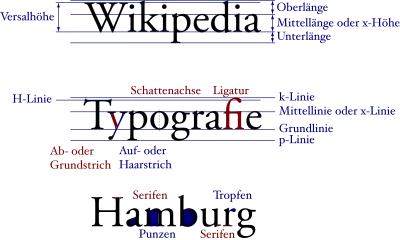
Die Mikrotypografie oder Detailtypografie ist die Gestaltung folgender Feinheiten des Schriftsatzes:
- die Gestaltung und Auswahl der Schriftart, die Verwendung von Kapitälchen und Ligaturen
- die Laufweite und Spationierung (das sind die Buchstabenabstände und Zeichenabstände), die Wortabstände
- die orthotypografisch korrekte Zeichensetzung
Der bei einem Leser bzw. Betrachter hervorgerufene Gesamteindruck des Schriftsatzes wird durch die obigen und weitere Faktoren bestimmt. Den subjektiven Gesamteindruck nennt man in der Fachsprache die Anmutung. Dabei wird durch die Gestaltung beim Leser auch ein emotionaler Eindruck erzeugt, was je nach Textsorte und Publikation sinnvoll sein kann und auch bewusst eingesetzt wird. In Massenmedien wie Tageszeitungen wird eher darauf geachtet, eine hohe Leserlichkeit auf Kosten einer – dabei auch nicht sachgerechten – emotionalen Wirkung der Gesamtgestaltung zu erzielen.[4]
Makrotypografie
Dies ist die Gesamtgestaltung eines Textwerks[5] (Buch, Druckseite, Textverarbeitungs-Dokument, Webseite usw.). Zu den Gestaltungselementen gehören unter anderem
- das Seitenformat,
- der Satzspiegel,
- Zeilenbreite, -abstand (Durchschuss) und -anzahl,
- das Vermeiden von unpassenden Worttrennungen und Absätzen,
- die Gliederung der Seite und des Textes,
- die Platzierung von Bildern und Tabellen im Text,
- das Mengenverhältnis der Schrift zu Bildern und Tabellen,
- die Schriftgröße und
- die Schriftauszeichnungen.
Grundelemente im Schriftsatz sind
- die Zeile für die horizontale Schreibrichtung,
- die Spalte bzw. die Kolumne für die vertikale Schreibrichtung (Spaltensatz).
Die einzelnen Elemente des Seitenaufbaus sollten sinnvoll aufeinander abgestimmt werden, wobei die Wahl der Schriftgröße sowie die richtige Positionierung von Abbildungen, Grafiken und Tabellen hierbei besonders wichtig ist. Die harmonische Aufteilung von bedruckter und unbedruckter Fläche ist entscheidend: Eine Seite darf weder überladen noch kahl wirken. Hilfreich ist hier die sogenannte Rastertypografie, bei der die typografischen Elemente nach einem vorgefertigten Gestaltungsraster angeordnet werden.
Eine verwandte Bezeichnung zur Makrotypografie ist Layout, wobei dieser Begriff in der Regel deutlich spezifischer verwendet wird.
Anwendung
Mithilfe von Typografie können der Inhalt, der Zweck oder die Anmutung eines Werkes verdeutlicht werden. Die Aussage eines Textes kann visuell unterstützt werden, wobei die gute Lesbarkeit i. d. R. an erster Stelle steht.
Zu den Anwendungsbereichen der Typografie zählt neben der Gestaltung von Mengentexten in Romanen oder Sachbüchern (Werksatz) vor allem der Akzidenzsatz. Dazu gehören Geschäftsdrucksachen (Briefblätter, Visitenkarten, Formulare), Werbedrucksachen (Flyer, Prospekte, Plakate) oder auch Familiendrucksachen (Einladungen, Gedenkkarten).
Bei der visuellen Erscheinung von Kommunikationsmedien versuchen Typografen meist die Gestaltung mit deren Inhalt (Botschaft) in Einklang zu bringen. Manchmal wird auch versucht, eine unterschwellig andere Botschaft (Subtext) zu vermitteln, die dem Inhalt des Textes durchaus widersprechen kann. Durch derartige Beeinflussung der Aussage eines Textes bzw. einer Botschaft kann einem Typografen die Rolle des Co-Autors zukommen.
Möglichkeiten typografischer Gestaltung sind traditionell der Einsatz unterschiedlicher Schriftarten, Schriftgrade/-größen und Auszeichnungsarten, die Wahl der Satzbreite (Zeilenlänge), des Zeilenfalls, des Satzspiegels innerhalb des Papierformates, die Zuordnungen unterschiedlicher Elemente zueinander im Layout, die Auswahl des passenden Papiers und vieles mehr.
Die Auszeichnungsarten dienen zum „Hervorheben“ einzelner Textstellen oder Absätze gegenüber dem Rest des Textes, z. B. wörtliche Rede oder Zitate. Wollen Typografen beispielsweise verdeutlichen, dass eine Textstelle das Gesprochene eines Protagonisten darstellt, dann kann sie kursiv dargestellt werden: Hermine! rief Harry …